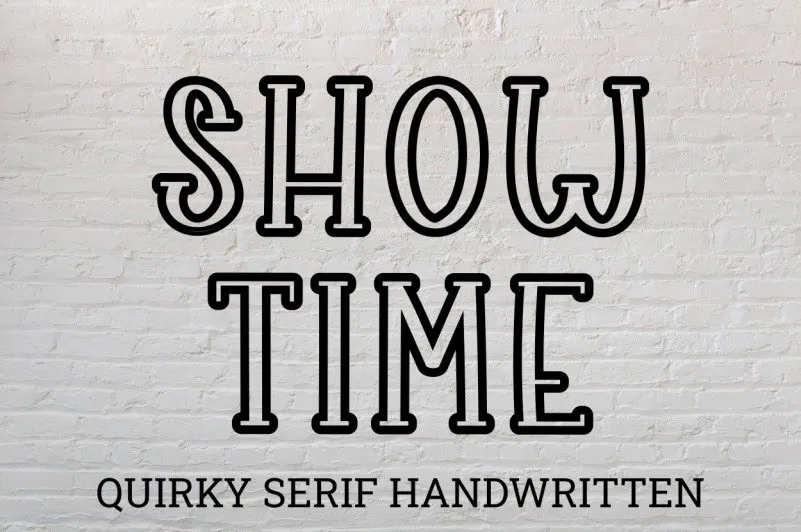
A Show Time Font é uma escolha perfeita para quem busca uma fonte exuberante e alegre que se destaca no meio do design. Esta fonte de display simples, mas leitora eficaz, oferece um tom ressaltado que permite destacar qualquer projeto. Este é um recurso valioso para o seu banco de fonts, pois tem potencial para elevá-lo em qualquer obra de arte ou criação. A sugiharto1790 criou uma fonte versátil e atraente com sua simplicidade e força visual, tornando-a uma opção primordial para aqueles que buscam trazer um toque único ao seu trabalho gráfico. Seja você um designer de logotipos, editor de fotos ou artista digital, a Show Time Font é o atalho perfeito para adicionar sua própria personalidade à cada projeto.